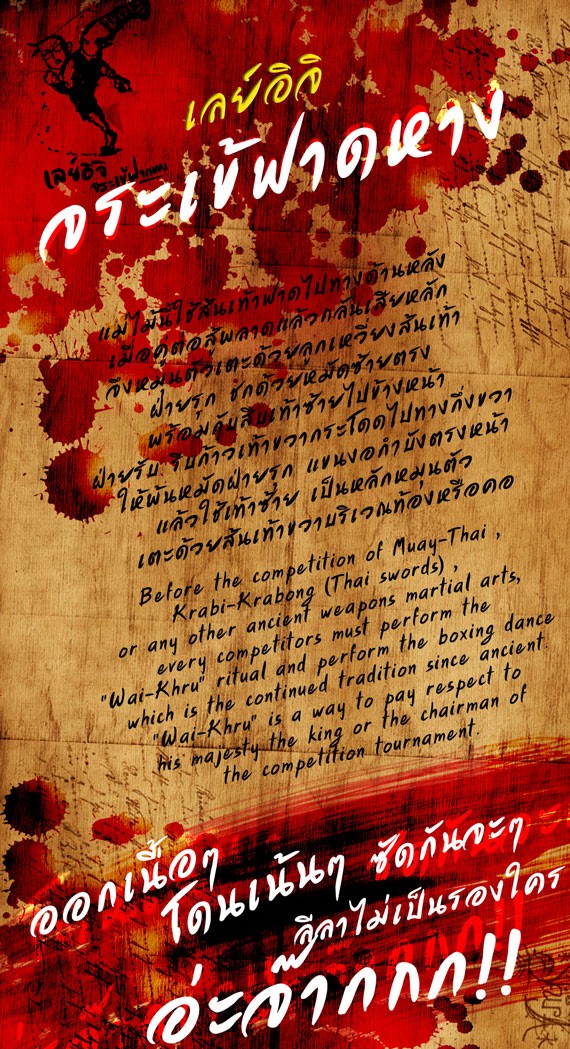
จากผลงานผู้สร้าง Layiji เล่นรุนแรง, Layiji ซารังเฮโย และ Layiji มหานิยม
ที่ได้รับการตอบรับอย่างล้นหลามในวงการการ์ตูนเสียวแปลไทย :05:
“เลย์อิจิ จระเข้ฟาดหาง” บทสรุปแห่งความสมบูรณ์ของวงการการ์ตูนเสียวแปลไทย :05:
ตัวนี้ผมอยากได้ฟิลลิ่งแบบฉวัดเฉวียน ตัวฟอนต์เลยออกลีลาตวัดเส้น ฉึบฉับ
พอทำไปทำมาก็เริ่มปรับแต่ละตัวให้เบาลง เพื่อจะให้ใช้กับตัวเนื้อความแล้วอ่านง่าย
แต่ยังติดความดิบอยู่นิดๆ อักษรบางตัวอาจจะทับๆ กันบ้างตามจังหวะ
เพื่อให้ดูแล้วเหมือนเป็นฟอนต์ลายมือหวัดๆก็ได้ (ลองดูจากบันทึกร่างฟอนต์ได้ครับ)
Layiji จระเข้ฟาดหาง